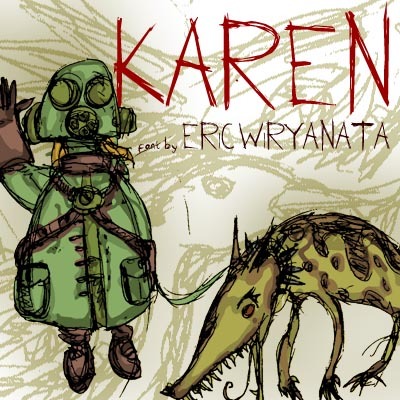
Karen_erc_2006 di Eric Wiryanata è un font *trash* gratuito che sembra graffiato su un muro con un pennarello rotto. Le lettere sono alte, frammentate e piene di inchiostro, con tratti irregolari che risultano grezzi e quasi squilibrati: somigliano più ad avvertimenti scarabocchiati in fretta che a una bella calligrafia. C'è un ritmo nervoso nella spaziatura che mantiene ogni parola vibrante e piena di carattere.
Usa Karen_erc_2006 per dare un tocco DIY audace a poster per concerti, cover horror, fanzine underground, grafiche streetwear, copertine di album e materiali di protesta. Questo font gratuito brilla nei grandi formati, dove i suoi bordi irregolari e le macchie d'inchiostro restano ben visibili; abbinalo a un sans serif geometrico pulito per i testi più piccoli, così da garantire la leggibilità mentre il titolo grida il suo messaggio.